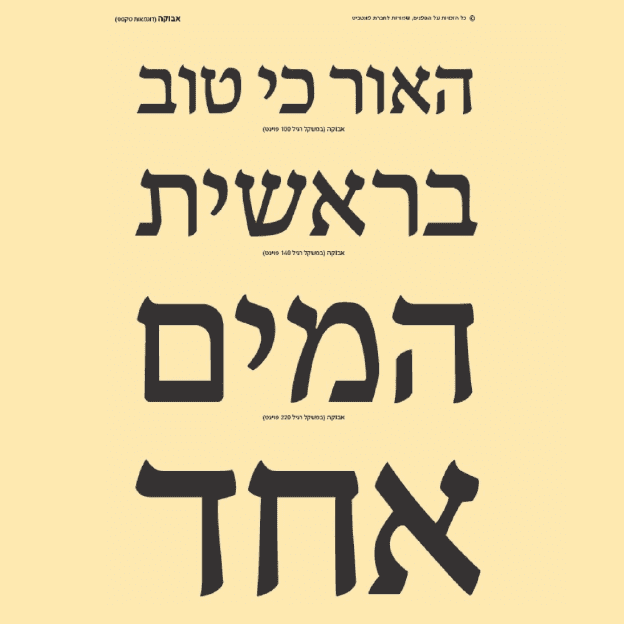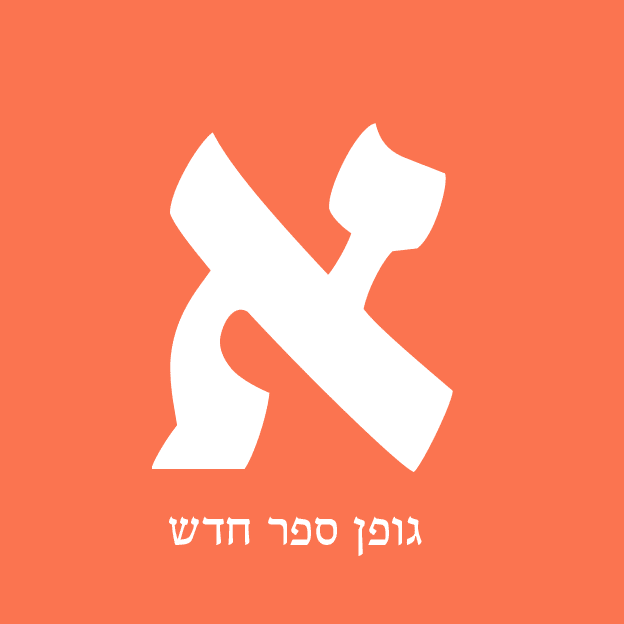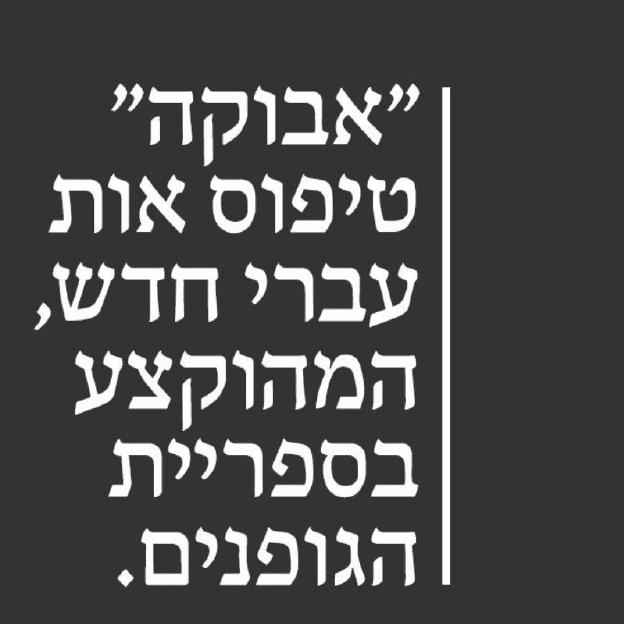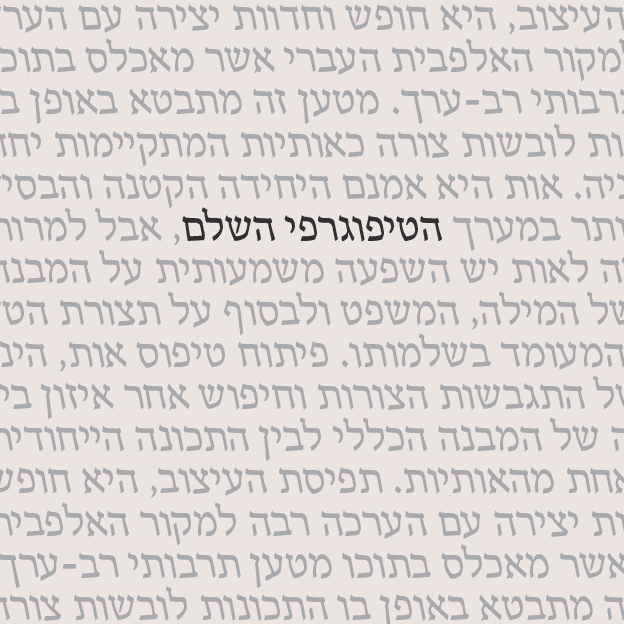
אבוקה
אבוקה / Fb Avuka
• שם הגופן:אבוקה
• מעצב הגופן:נדב עזרא
• סגנון:סריף
• קטגוריה: עברית ספר מקורות
• מאפיינים: רגיל נטוי כבד כבד-נטוי
• תכונות: אלגנטי מגזיני מעוגל עדין פשוט קלאסי רוחני
סיפור הגופן:
אות ספר חדשה שאותה פיתחתי מתוך תפיסה של ריבוי התכונות, כזו שמובילה דווקא להרחבת התחושה האוניברסלית הפשוטה, שהיתה עבורי לעמוד התווך בתהליך הגיבוש של טיפוס האות ׳אבוקה׳. זוהי אות שמשלבת בתוכה חדות וקלילות כמו שמתקבלת עם הגופן ׳דוד׳, לצד קשיחות ריבועית ושורשיות תרבותית אשר מאפיינת את הגופן ׳הדסה׳, ובנוסף נגיעות של חיטוב בשיפולים ורכות של מכחול בסריפים, שמוכרים לנו מהגופנים ׳פרנקריהל׳ ו׳נרקיסים׳. ׳אבוקה׳ הוא גופן פשוט ומכבד, בעל עושר הרמוני מוצנע, מתאים לעימוד של ספרים ומגזינים וגם נותן מענה מקצועי, לקריאה של טקסט על גבי מסכים.